Anna Carreras, 2017
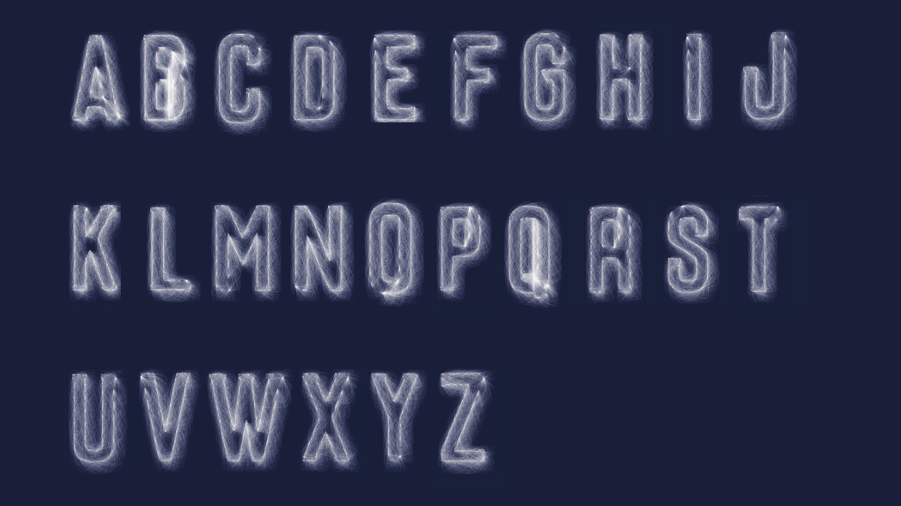
Relevancia
Esta investigación se presenta como una serie de talleres sobre la creación de tipografías mediante código, principalmente con Processing. El trabajo se centra en un enfoque donde el diseñador define un sistema de reglas y parámetros que permiten generar infinidad de variaciones formales de los glifos.
La principal aportación de estos experimentos es eminentemente metodológica. Investiga la tipografía no como un objeto estático y cerrado, sino como un sistema dinámico y generativo, cuyo resultado visual emerge de las reglas establecidas en el código.
Aunque se trata de una serie de talleres, su relevancia reside en la figura de Anna Carreras, una de las pioneras del arte generativo y el diseño interactivo en España. Su trabajo demuestra un modelo de diseño donde la autoría se desplaza de la creación de la forma final a la creación del sistema que la genera.
Clasificación
- Década: Década de 2010
- Función: Exploración formal y/o performativa
- Contexto: Investigación / Experimental
- Grado de interactividad: Interacción generativa
- Input multimodal: No
- Tipo de input: Periféricos convencionales
- Tipo de output: Transformación morfológica
- Tecnología empleada: Processing
- Alfanumérica: Sí
- Mantiene codificación textual: No